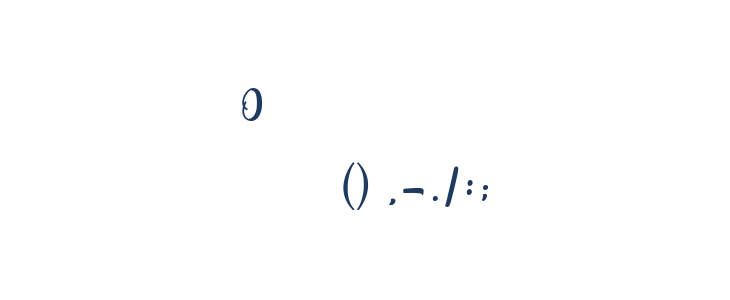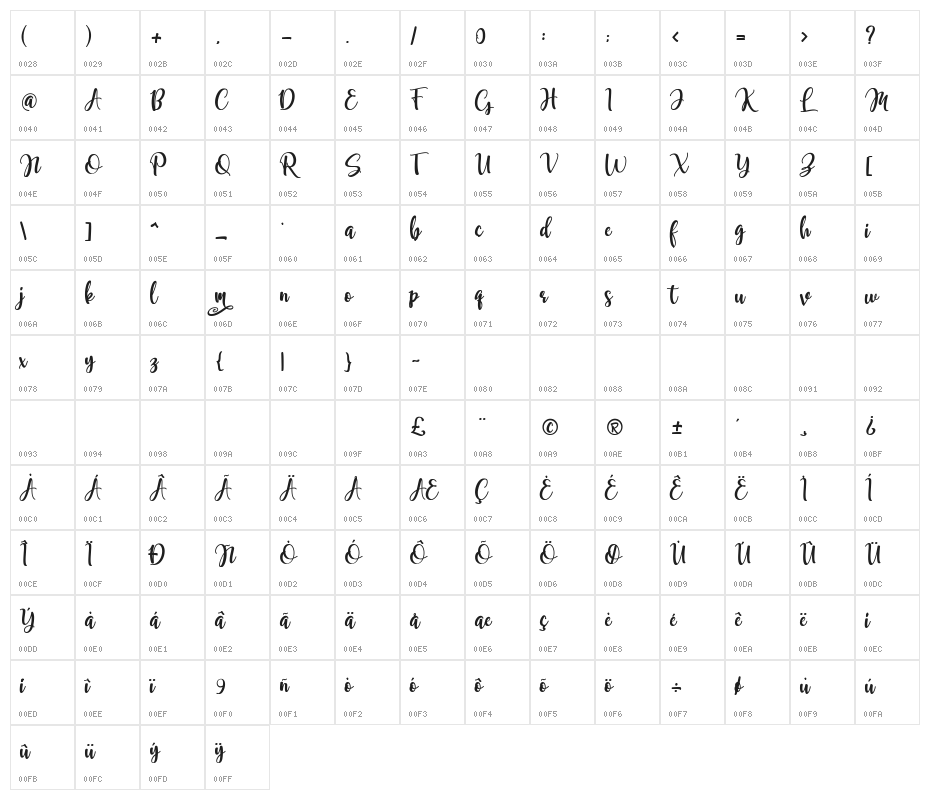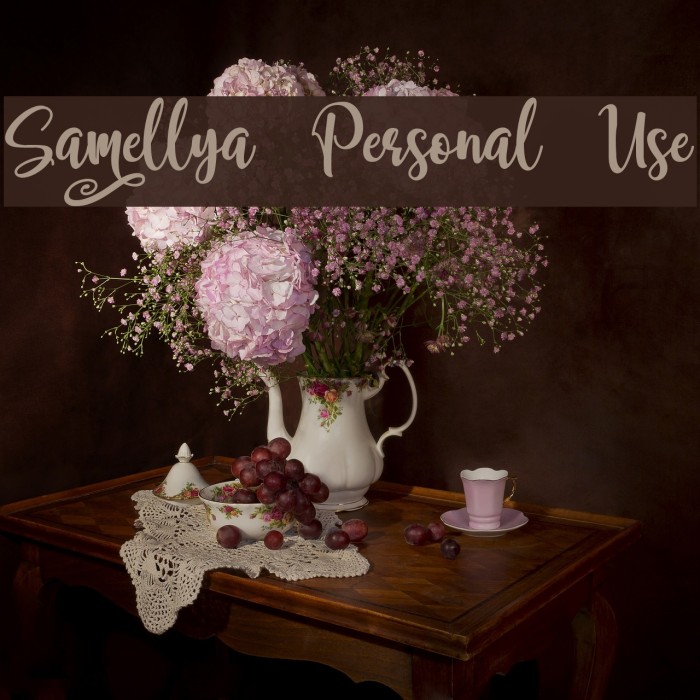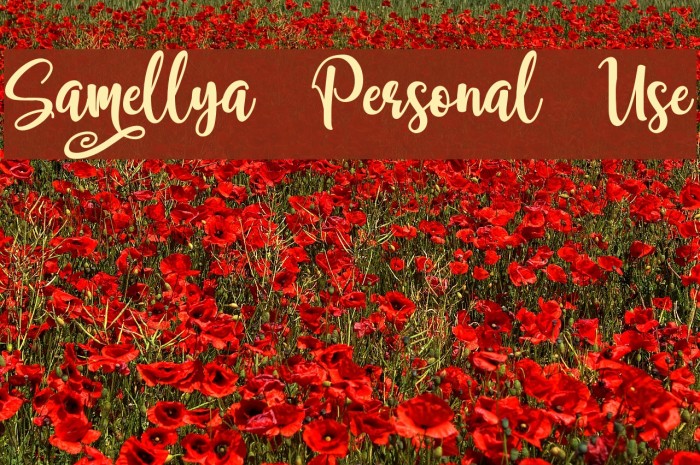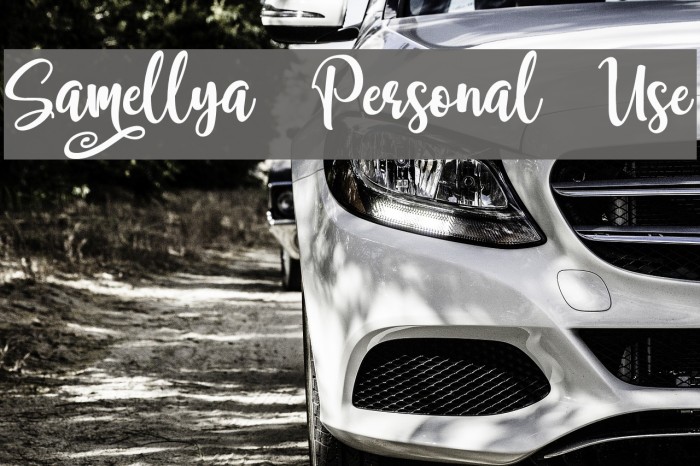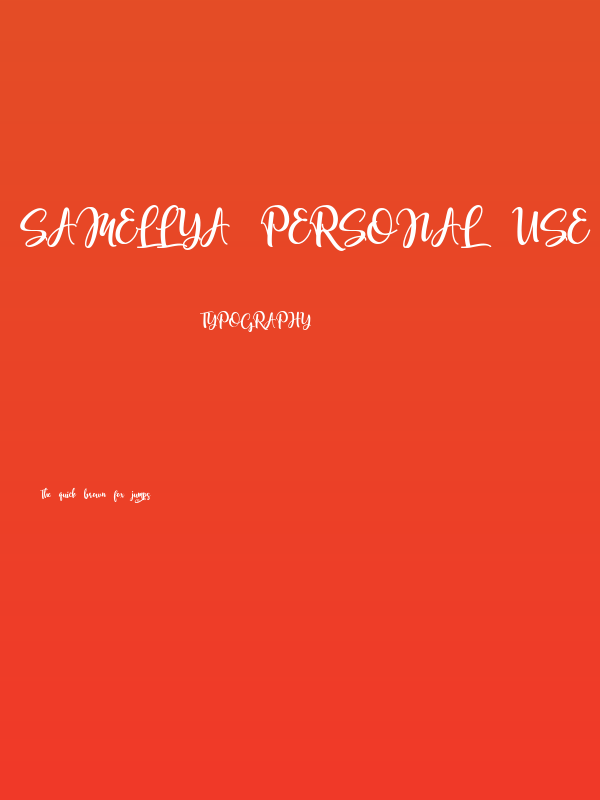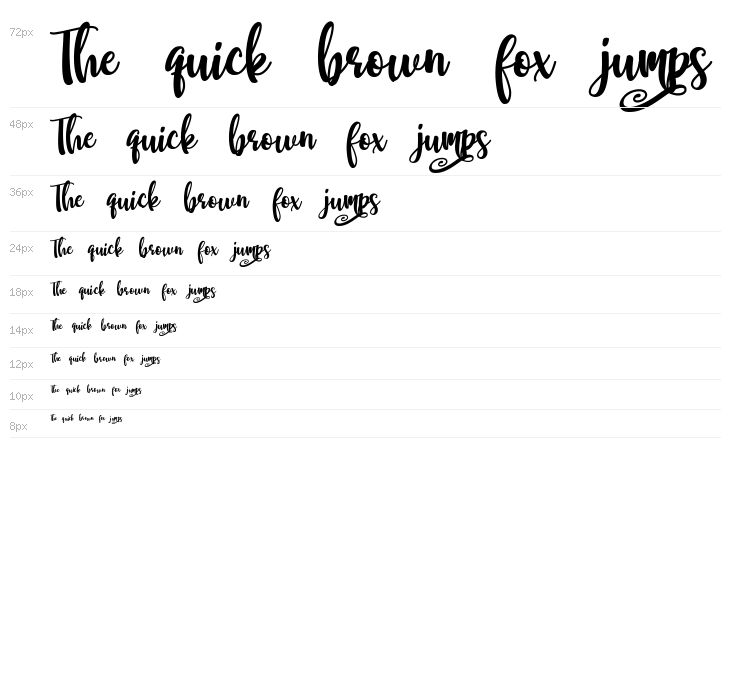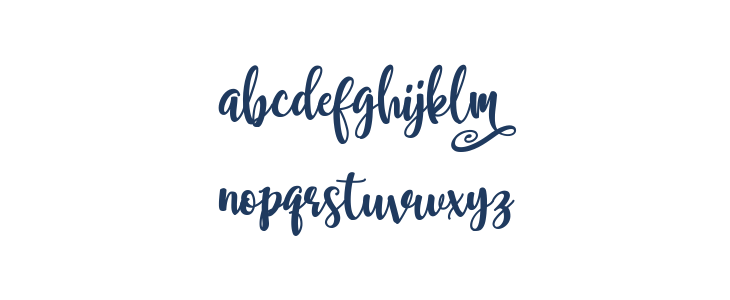
Samellya Personal Use Font
✎ Script
| Anwendungsfall | Logos, Invitations, Decorative text |
| Vorgeschlagene Projekte | Ideal for wedding invitations, greeting cards, branding, and logo design where a personal, artistic touch is desired. |